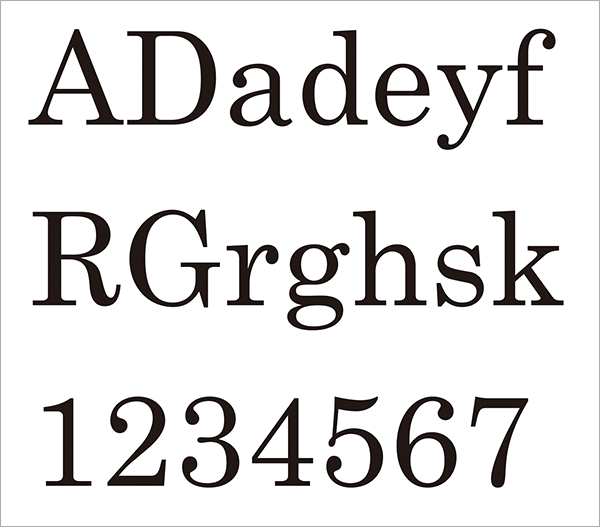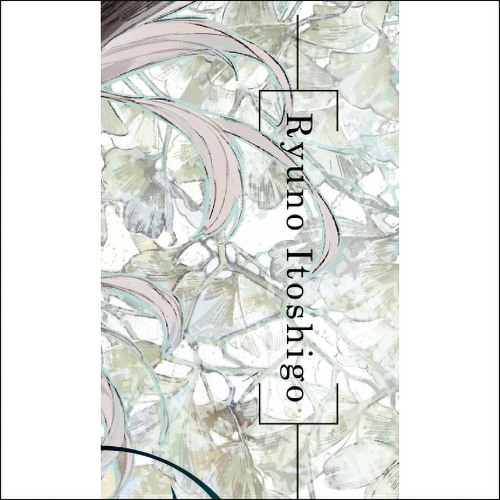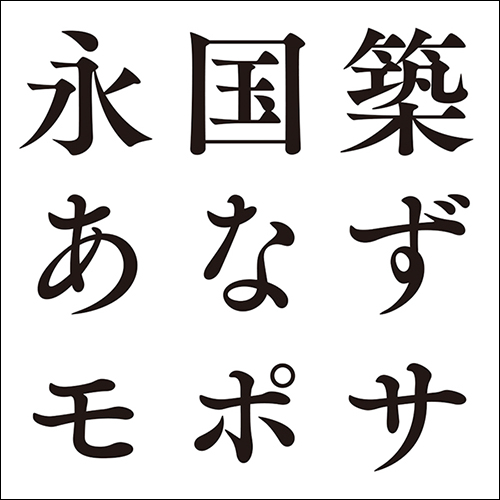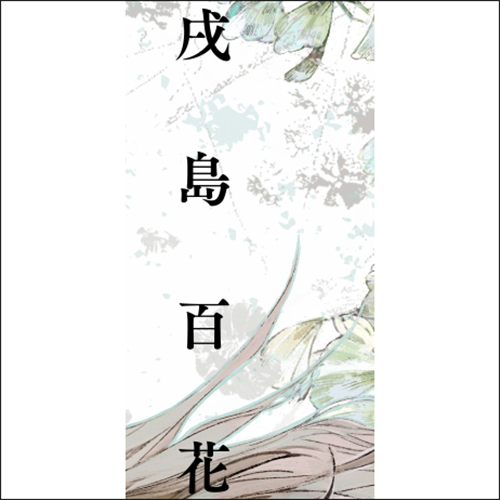
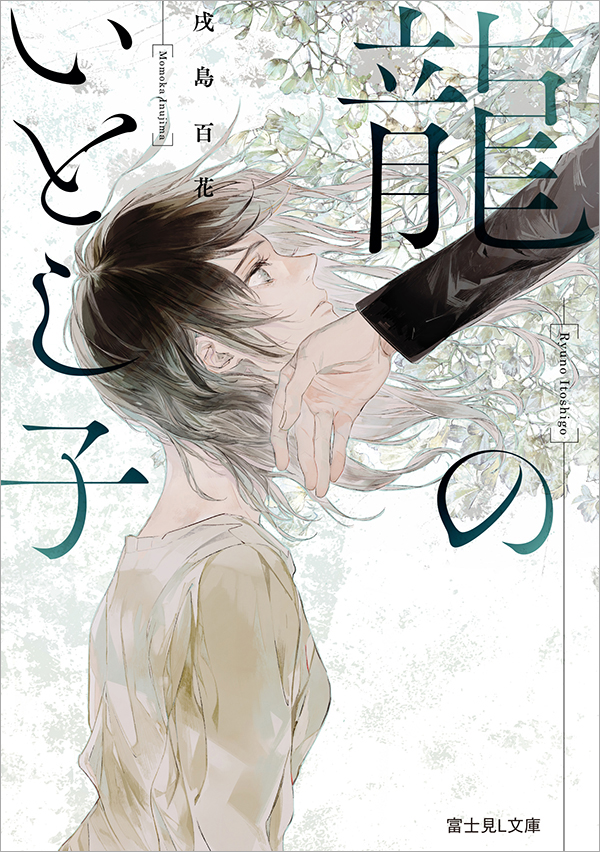
●Designer:團夢見[imagejack]
●Illustrator:ハルカゼ
今回は文庫『龍のいとし子/戌島百花』の使用フォントをご紹介。本記事はデザイン構成において重要な「フォント」の選定プロセスや加工方法を、貴重なプロの実例から紐解いてデザイン制作に役立てる連載です。
流れるような筆致の文字で繊細な世界観を表現
拝み屋をしていた父の死をきっかけに異形に襲われるようになった女子大生の柚葉と、彼女を守り助ける美貌の男子高校生の周を主人公にした恋愛ファンタジー小説の表紙カバー。美しき人外と少女の禁忌の恋をテーマにした幻想的な作品世界が、繊細でありながら表情豊かで躍動感にあふれるイラストとタイトル文字などで表現されている。
Font.01「筑紫Bヴィンテージ明朝L-R」
繊細な作風を意識して流麗で味わい深い明朝体に
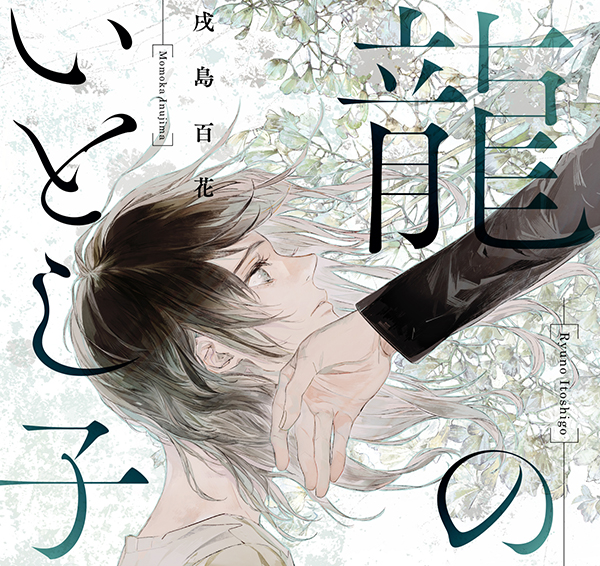
メインタイトルの文字は、明治4年に発刊された「手習の文/福澤諭吉編」(慶應義塾出版)の「ふ」のデザインにインスパイアされたという古風な雰囲気ながら独創的なニューテイストの明朝体「筑紫Bヴィンテージ明朝L-R」(フォントワークス)。繊細で幻想的な作品の雰囲気に合わせ、若干文字を細めたうえで使用されている。
Font.02「筑紫Aオールド明朝 B」
タイトルロゴに合わせ美しいフォルムの明朝体に
作者名「戌島百花」部分の文字は、美しい打ち込みや伸びやかなハネなどが特徴的なオールドスタイルながら新しさもある明朝体「筑紫Aオールド明朝 B」(モリサワ)。メインタイトルとの相性や読みやすさを意識して、書風が近くよりオーソドックスな書体が選択された。
Font.03「Century Schoolbook Roman」
シンプルなセリフ体で全体の雰囲気を引き締める
タイトルの欧文表記「Ryuno Itoshigo」部分はオーソドックスなセリフ体「Century Schoolbook Roman」(Monotype)が選択された。シンプルなセリフ体をアクセント的に用いることで、全体の雰囲気を引き締めるのが狙い。